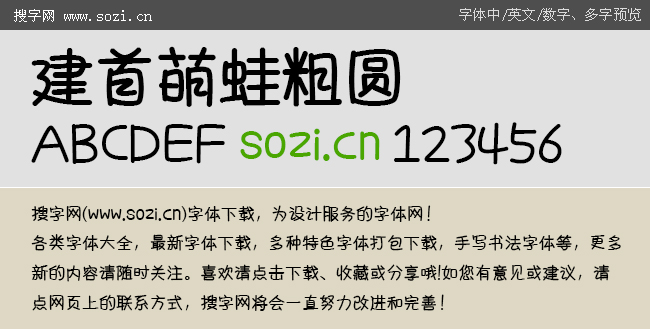
建首萌蛙粗圓
搜字網(wǎng)提供一款建首萌蛙粗圓中文字體下載,建首萌蛙粗圓是一套卡通風(fēng)格的POP字體。字體筆畫粗壯醒目,字形為卡通風(fēng)格,充滿童趣,看上去非?蓯邸_m合兒童包裝設(shè)計(jì)、海報(bào)設(shè)計(jì)、廣告設(shè)計(jì)等應(yīng)用。